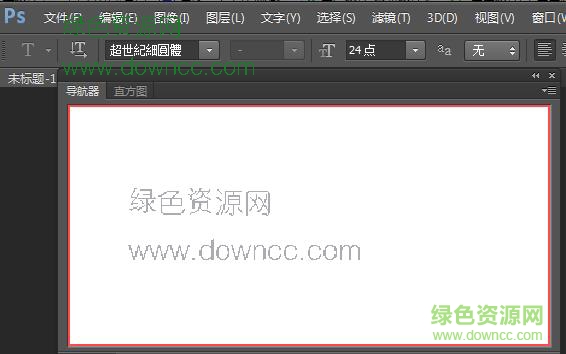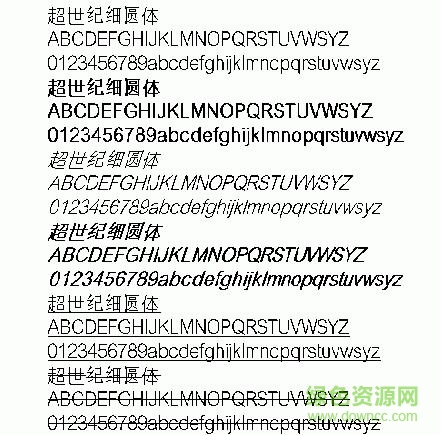
软件介绍 软件标签: 超世纪细圆体 超世纪字体 超世纪细圆体是一款很好看的字体文件,能够应用到众多编辑器中进行文字编辑与艺术字编辑,还能够添加上各类效果进行二次加工制作成满意的效果文字状态,在众多字体中广受用户的喜爱!需要的用户快到绿色资源网下载体验吧!字体介绍超世纪细圆体是一款十分流行的字体,该字体线条粗细均匀,看上去很清爽,十分美观,整体效果非常统一,且字库完整,可以广泛应用于名片设计、海报、宣传册、电影、电视台广告以及内容用字等领域,有需要的朋友可以免费下载收藏。使用说明1.需要通过安装方可使用2.请将在绿色资源网下载的字体文件拖动到C:\Windows\Fonts文件夹下即可 软件截图 上一张下一张(1 / 1) 安装详细截图 猜你喜欢 圆体字体 圆体字体 圆体字体是一款整个字形偏圆的字体类型。该类字体所有的拐角全部为圆弧形,没有直角,如:超研泽细圆体、华康中圆、迷你简粗圆等,都是典型的圆体字体,喜欢的朋友,赶快下载体验吧! 查看更多>> 华康粗圆体字体 3.07M/中文/10.0/下载 造字工房雅圆体字体 1.33M/中文/10.0/下载 造字工房悦圆体字体 1.71M/中文/0.0/ttf版下载 义启简圆体ttf 1.41M/中文/2.7/下载 胡晓波趣圆体字体打包 218KB/中文/5.0/下载 叶根友圆趣卡通体 1.30M/中文/5.4/免费版下载 其他版本下载 标题 大小 更新日期 下载 下载地址 电脑版 超世纪细圆体字体 点击报错 软件无法下载或下载后无法使用,请点击报错,谢谢! 关闭报错反馈 请描述您所遇到的错误,我们将尽快予以修正,谢谢! *必填项,请输入内容 本类最新 jetlink boldsemiblack 字体 超世纪粗颜楷字体繁 超世纪粗毛楷简体 超世纪粗仿宋简体 超世纪粗古印(繁) 超世纪粗仿黑字体 相关文章 Photoshop字体安装使用方法和技巧 如何解决“无法新增字体”问题 Win 7系统安装字体方法 网页字体大小设置方法 怎么改网页字体大小 在Linux系统中安装字体的几种方法 windows7字体显示问题:打开某些程序的时候显示的是乱码 用户评论 热门评论 最新评论 发表评论 查看所有评论(0) 昵称: 请不要评论无意义或脏话,我们所有评论会有人工审核. 字数: 0/500 (您的评论需要经过审核才能显示)